- 金剛黒体「バリアブルフォント/ゾンカ語/簡体字中国語Bold」や 「シン・かなデザイン」の新書体など、 実りの文字の秋となる合計24書体を ダイナフォント全書体が使える年間ライセンス 「DynaSmart V」に11月24日から提供開始
ダイナコムウェアは、ダイナフォント年間ライセンス「DynaSmart V」「DynaSmart 教育機関向けプラン」「DynaSmart 学生版」を契約ユーザーに向けて、DynaFont(ダイナフォント)2022年新書体として、ダイナコムウェアのフラッグシップフォントである「金剛黒体(ルビ:こんごうこくたい)」のバリアブルフォント「金剛黒体 VF(バリアブルフォント)」、新多言語「金剛黒体 ゾンカ語」、新ウエイト「金剛黒体 簡体字中国語Bold 6ウエイト」、シン・かなデザイン「古籍真竹B(ルビ:こせきまだけビー)」「龍門石碑体A(ルビ:りゅうもんせきひたいエー)」、毛筆系初のテロップ書体「大河体S(ルビ:たいがたいエス)」など、“実りの文字の秋”とも呼ぶべきダイナフォント合計24書体を2022年11月24日(木)より提供を開始した。
その他の提供書体として、オーソドックスな行書として様々な場面で活用されている「行書体」のOpenTypeフォントPro1-6/1-6N版や、楷書と行書の中間を目指した革新的な毛筆系書体「松月虹(ルビ:しょうげっこう)」のTrueTypeフォント版も追加収録していた。
呼吸するバリアブルフォント「金剛黒体 VF(バリアブルフォント)」
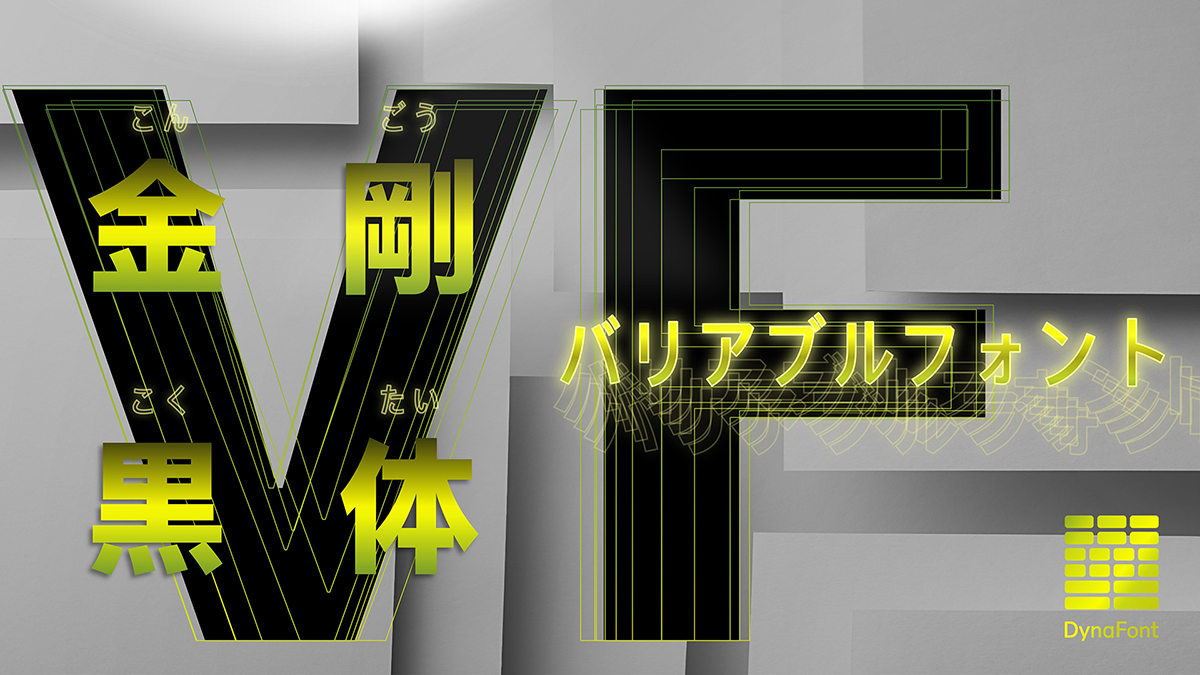
「金剛黒体 VF」は、シームレスなウエイトと横幅の調整が可能なバリアブルフォント。
ユーザーは独創性を駆使して、フォントの太さ・細さ・広さ・狭さを調整することで、自分だけのレイアウトを創造できる。
Adobeシリーズのソフトウェアを例に挙げれば、文字パネルのバーをスライドすることにより、太さや幅などを自由に調整できる。
ダイナコムウェア独自のフォントツールで開発された「金剛黒体 VF」は、さまざまなレイアウトテストや最適化を行うことで、快適な読み心地を実現した「金剛黒体」の品質を損なうことなく、繊細で滑らかな変化を提供する。
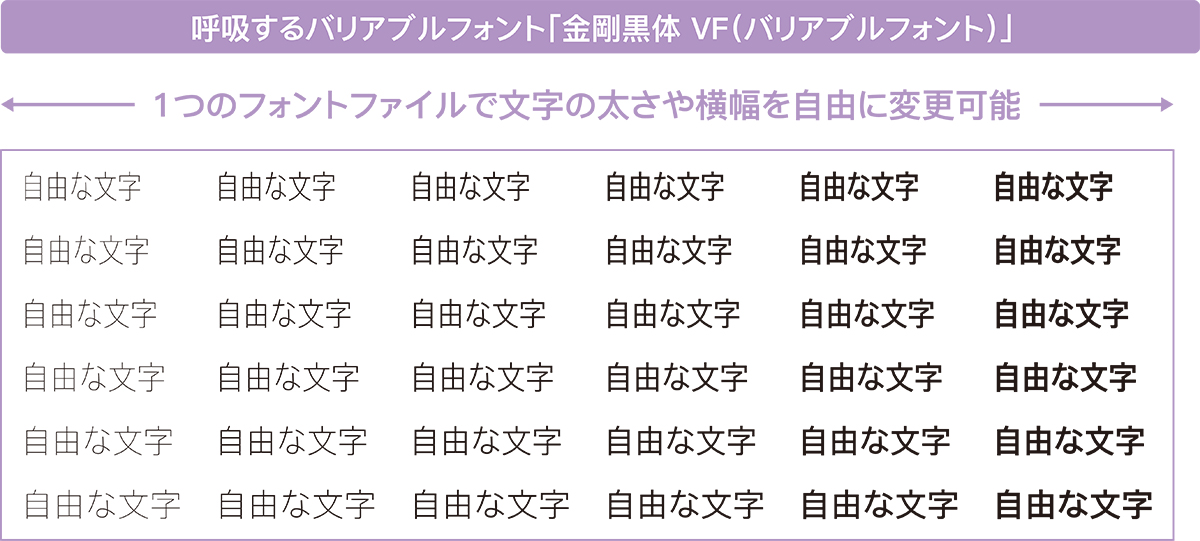
新多言語「金剛黒体 ゾンカ語」
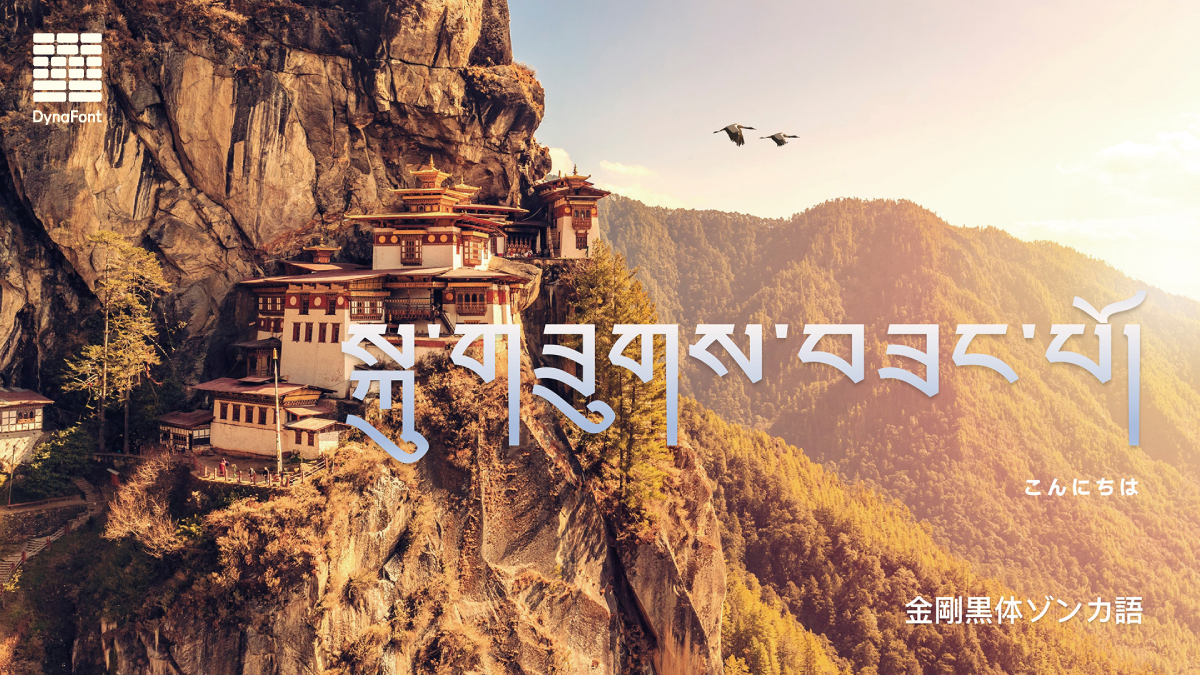
「ゾンカ語」はブータンの文字であり、中華人民共和国のチベット自治区の文字と共通している。
「金剛黒体 ゾンカ語」は、曲線の柔らかさと幾何学的な美感と筆画の一致性を追求した「金剛黒体」のスタイルと一致させながらも、ゾンカ語の文字の独特な手書き感も再現した多言語フォント。
シンプルでありながら、堅さも柔らかさも感じさせるデザインは、理性と感性のバランスが絶妙で、なおかつ素晴らしい読み心地を備えている。
「金剛黒体 多言語」同様に6ウエイトに対応しています。また、グリフの組み合わせ変換機能がフレキシブルな組版効果をもたらし、母語話者の自然な読む習慣にも最適な書体となる。
新6ウエイトを追加「金剛黒体 簡体字中国語」
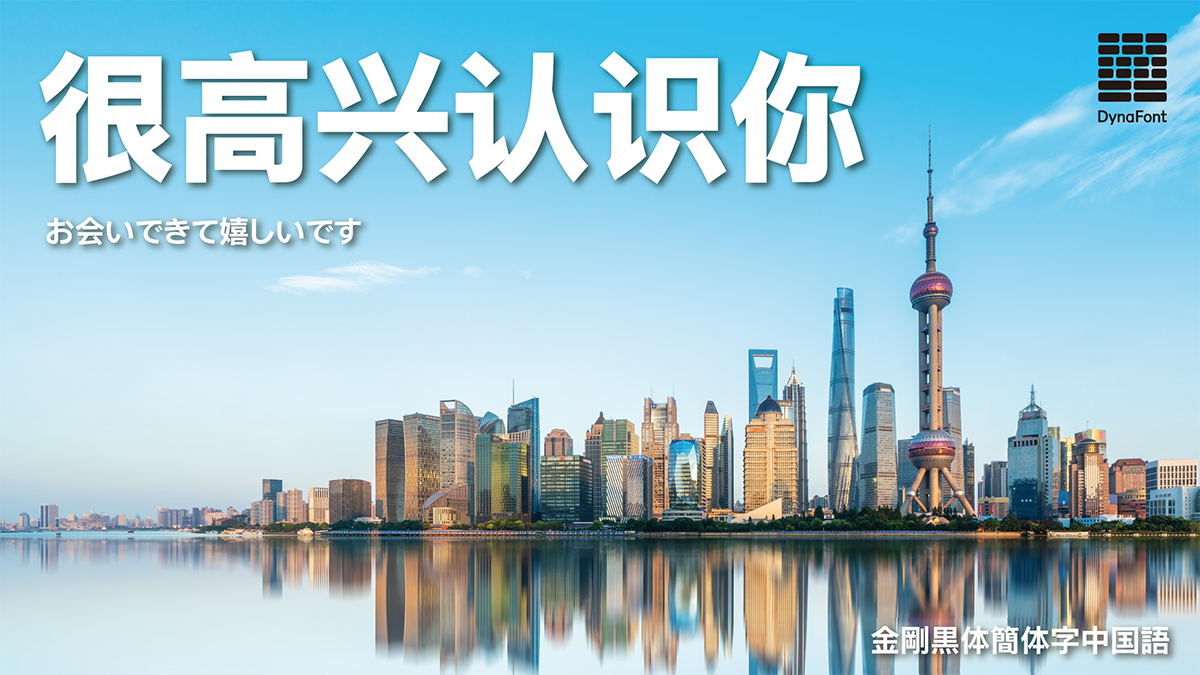
「簡体字中国語」は、中華人民共和国で制定された従来の漢字を簡略化した字体で中国大陸のほかシンガポールやマレーシアなどで使用されている言語。
「金剛黒体 簡体字中国語」は、毛筆で書いた時のような趣とシンプルなデザインをバランスよく融合させることで高い視認性と可読性を実現しました。2022年4月に先行して12ウエイトに対応した「金剛黒体 日本語」に続き、「金剛黒体 簡体字中国語」もBold、Extrabold、Ultrabold、Black、Extrablack、Ultrablackの6ウエイトを、それぞれの太さに合わせた読み心地を追求した設計にてリリースした。
※簡体字中国語のBoldからUltrablackの6ウエイトは「SC14(GB18030対応)」のみの対応となる。
シン・かなデザイン「古籍真竹B」「龍門石碑体A」
シン・かなデザインは、ダイナフォントの魅力を改めて掘り起こし、皆さまにも書体の魅力を再発見いただける試みとなる。
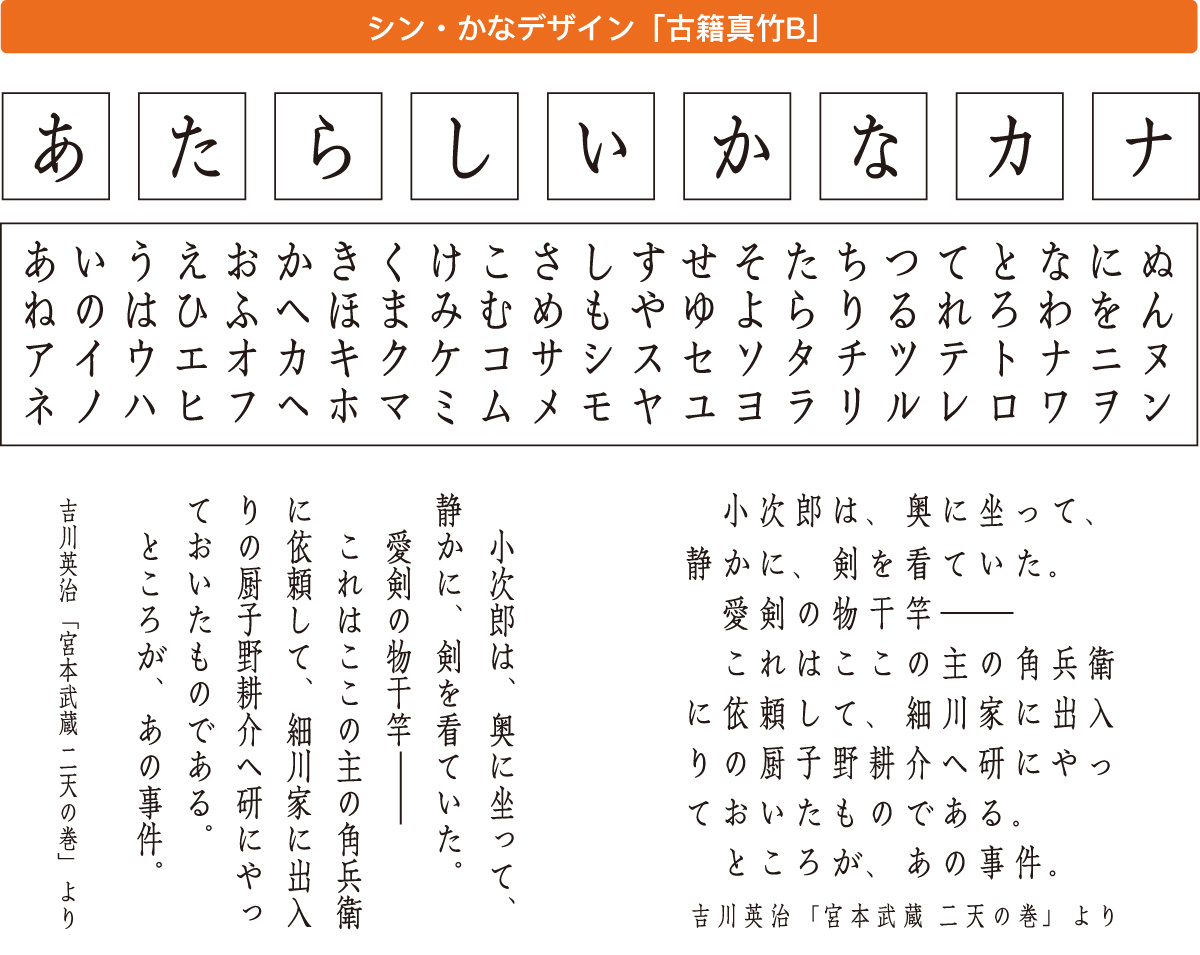
「古籍真竹B」は、ストロークの転折が竹の節のような力強さとしなやかさが特長の「古籍真竹」から、かなをリ・デザインすることで、よりクラシカルな趣きを追求した古籍書体。
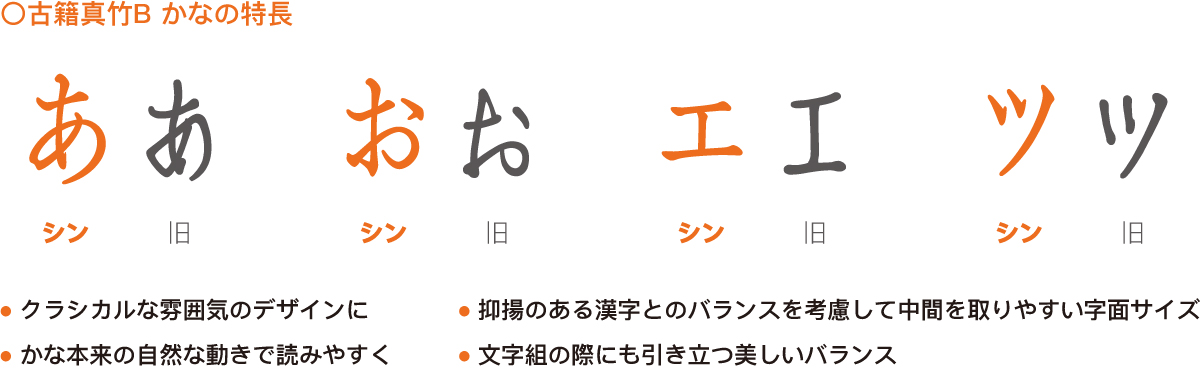
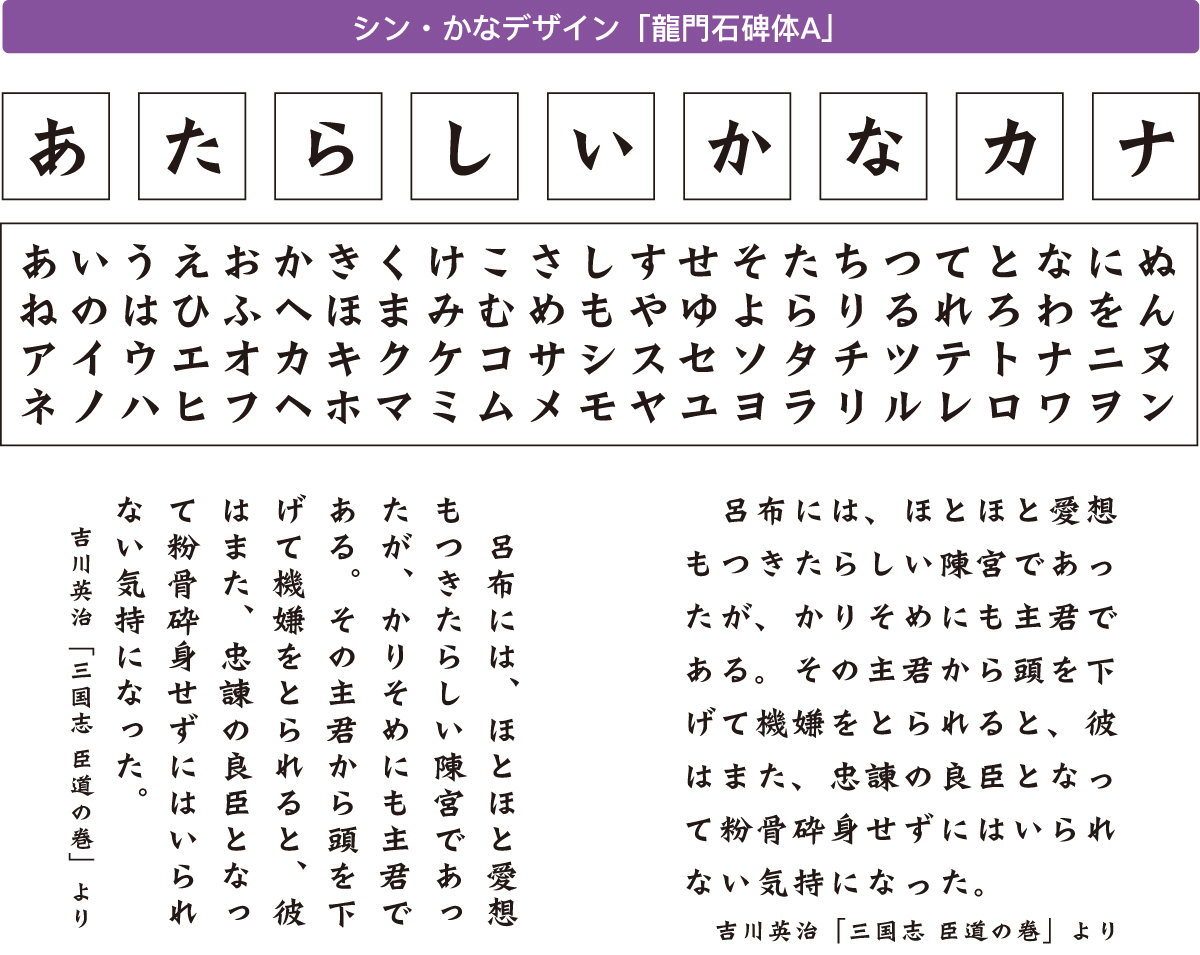
「龍門石碑体A」は、力強さと独特の風格を備えた中国の龍門石窟に刻まれた文字の書体様式と特長を持った書体「龍門石碑体」から、かなをリ・デザインすることで、より漢字部分の特長に近づけた書体。
豪快な運筆で迫力あふれる毛筆系テロップ書体「大河体S」
「大河体S」は、DF大河体をベースに、画面のあらゆるサイズでの表示に対応した書体として再設計したテロップ書体。
「大河体S」のベースになった大河体は、筆文字ならではの勢いや力強さを表現した女性書道家による毛筆系書体となる。
筆は鼬(いたち)の毛の筆を使用しており、その特徴である優れた弾力性が、起筆や払いの勢いに見事に反映されると共に、流れるような筆運びにも色濃くあふれている。
豪快かつ極太な筆画の中に、どことなく繊細さや柔らかさも感じさせる文字は、タイトルや見出しにおいて大きな存在感を与えることだろう。
「大河体S」は、ベースになった大河体の特長を引継ぎ、画面表示においても豪快な運筆による墨文字ならではの確かな迫力を演出する。
秋の夜空に架かる虹のように伝統と現代をつなげる革新的な毛筆系書体「松月虹」
「松月虹」は、楷書と行書の中間を目指し、伝統的な書道の規範に縛られず独特な書きぶりで現代感を表現した革新的な毛筆系書体。
優雅にして明快な字形で流れるような運筆の中においても随所に硬さの残る筆使いを調和させることで剛柔合わせ持った様は、さながら神秘的な月虹に優しく照らされ浮かび上がる松の木のよう。